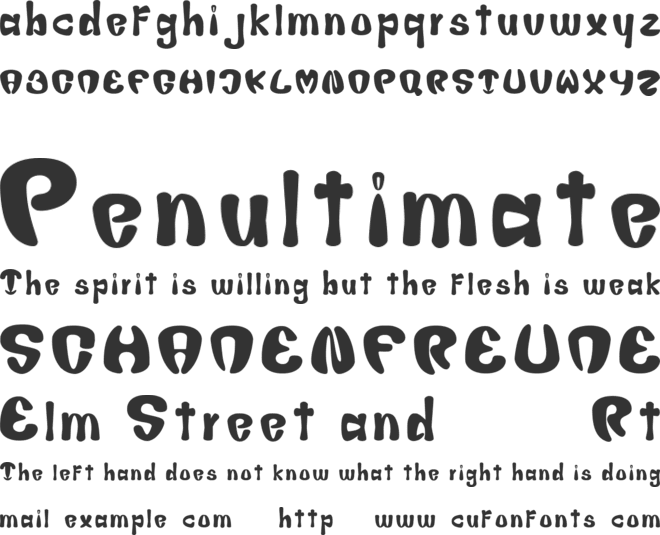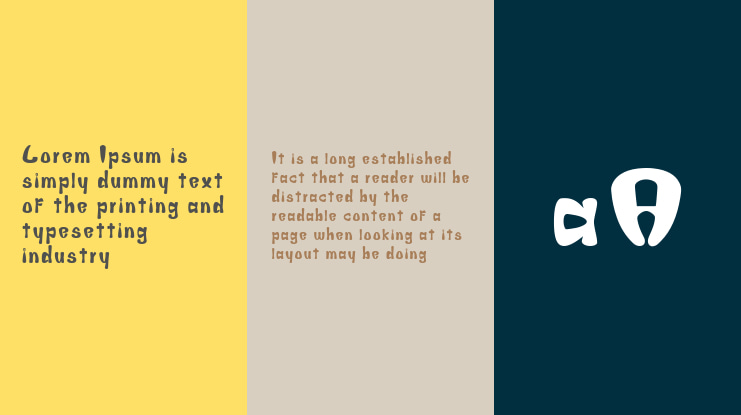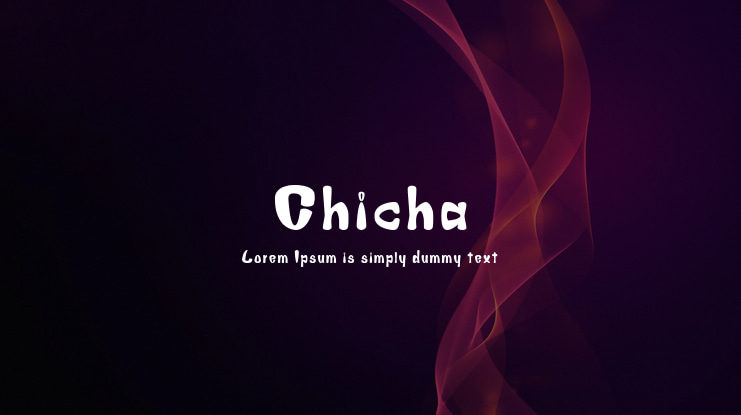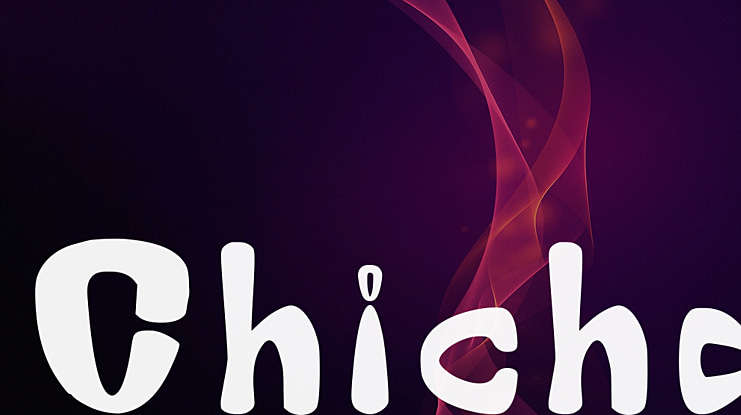
Chicha Font
Tipografía chicha. Esta tipografía nace de una conceptualización del pueblo Pijao en la región del Tolima, en Colombia. Se toman elementos primordiales dentro de su cultura, agricultura en específico, de esta forma se exalta el Maíz como dieta primordial. Se abstrae rasgos del maíz para dar forma a la tipografía.
Typography of chicha. This typography is a conceptualization of the Pijao people in the Tolima region of Colombia. The primordial elements within its culture, agriculture in a specific place, the primordial form. The features of corn are abstracted to give shape to typography.